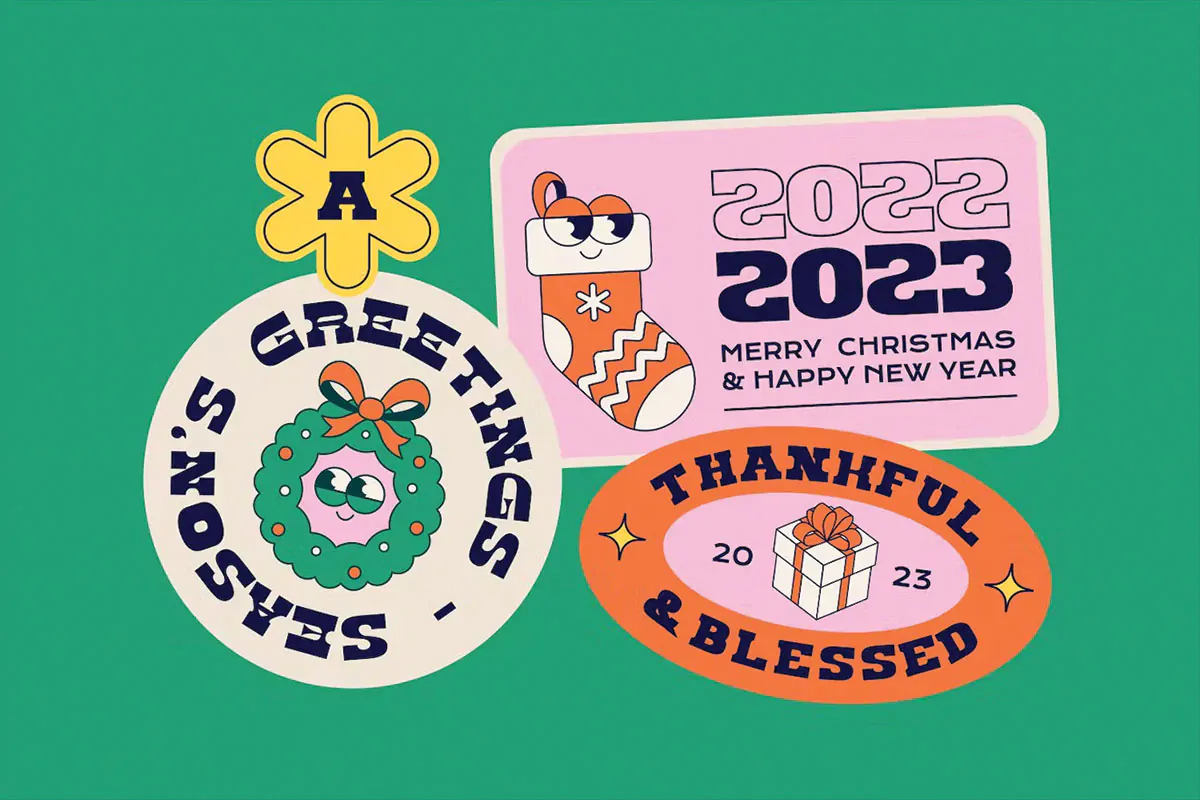
فونت منحنی شیک و مدرن Twin Denko
فونت منحنی شیک و مدرن انگلیسی
فونت منحنی شیک و مدرن Twin Denko یک قلم سنس سریف انگلیسی انحنا دار است که مناسب جهت استفاده در طرح و پروژههای گرافیکی مختلف میباشد. این فونت زیبا با وزن معمولی طراحی شده است که میتوانید از آن در طراحی پوستر، بسته بندی محصولات، ظروف یکبار مصرف، لوازم التحریر، کاور آلبوم موسیقی و … استفاده کنید.